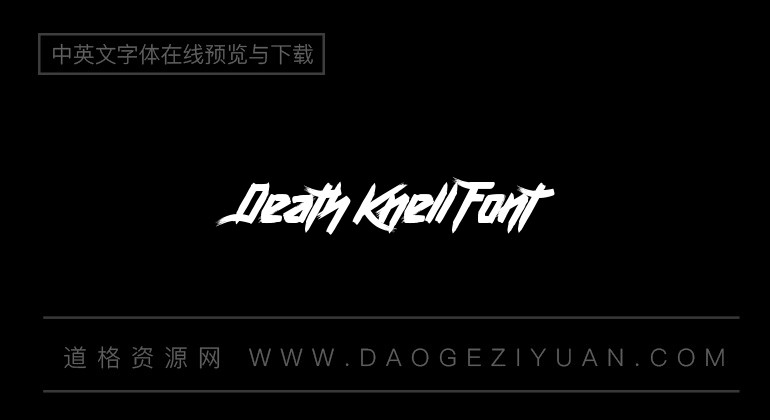
Death Knell Font
Death Knell Font 是一种手写的黑体字体,其中包含有 52 个字符,包括大写字母、小写字母、数字和标点符号等。这种字体的设计风格非常独特,具有强烈的手写风格,适合用于一些设计项目中,如海报、书籍封面、标志和插图等。字体的设计师为 Paul Grosse,他在设计这种字体时,参考了一些传统的手写字体,并加入了一些自己的创意,使得这种字体更加的有趣和独特。 Death Knell Font 的特点是粗体和黑色,使得它非常适合用于需要强调的文本和标题。
Death Knell Font是一款非常不错的手写艺术字体,具有很好的视觉感,适合于文化类的宣传设计、商业类品牌的广告和产品包装设计以及个性化文字排版等较多场景。